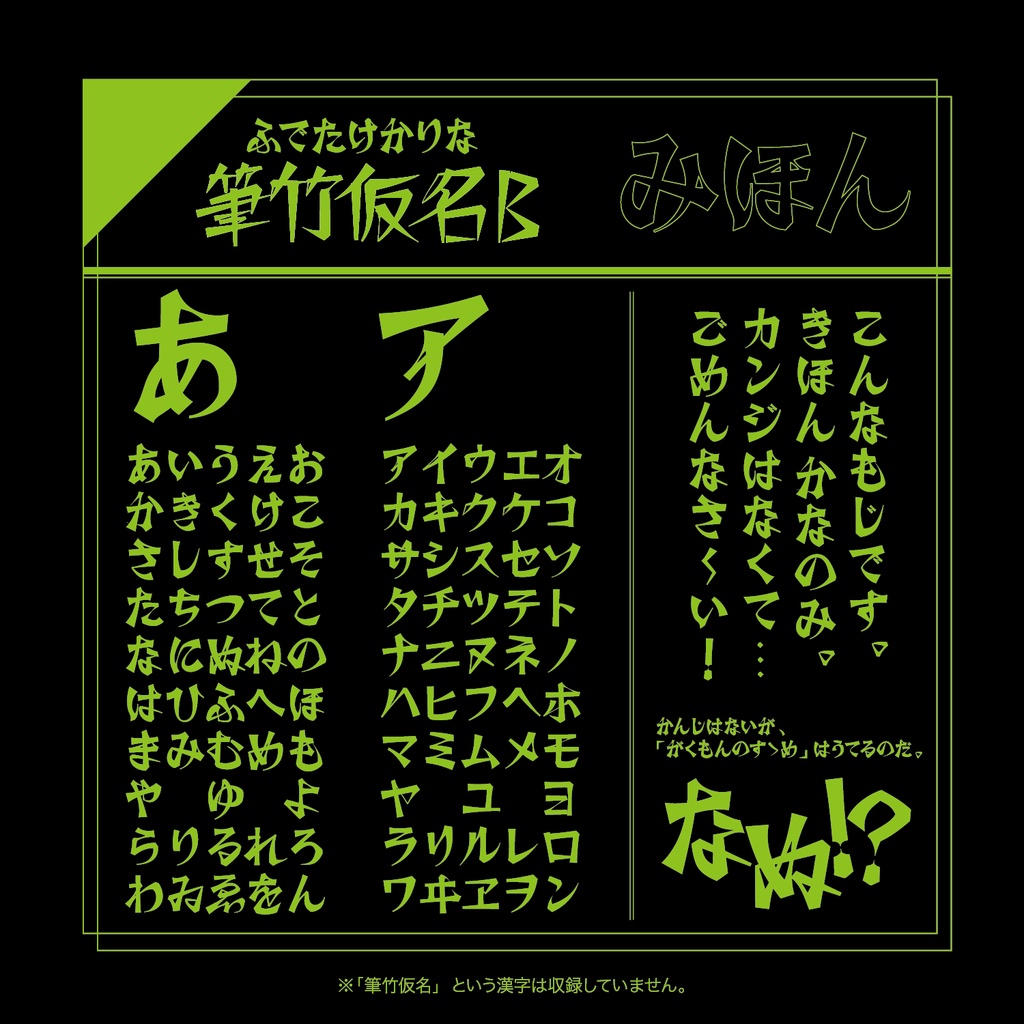
【フリーフォント】筆竹仮名B
<内容> ・「.otf」形式のフォント(Mac用) ・「.ttf」形式のフォント(Windows用) ・readme 【このフォントについて】 筆書体らしい運筆の特徴をもちつつ、ゴシック体のように角張ったパーツで構成されるフォントです。 かな書体のため、インパクトを持たせたい場面で部分的に使用すると効果的だと思います。 無償利用・商用利用問わず、自由にご使用いただけます。 印刷物のみならず、ゲームやWebなど何にでもご活用ください。 当フォントを利用した制作物などを、X(旧:Twitter)で報告していただけると、とても励みになります。 不具合の修正や新しいグリフの追加が行われていますので、最新のバージョンをご確認ください。 【すずみばと書林】 《もじピジョン》と《Suzumi Designs》による2人組のフォント制作ユニットです。 共同制作のフォントを配布・販売しています。 「書林」は本来「多くの書籍が集まるところ」という意味ですが、ここでは「多くの書体が集まるところ」という意味を込めて名付けました。 新作フォントの公開やバージョンの更新情報はそれぞれのTwitterでアナウンスしています。当フォントダウンロードの折には、フォローしていただけると幸いです。 《すずみばと書林/BOOTH》https://suzumi-bato.booth.pm/ 《もじピジョン/Twitter》https://twitter.com/Moji_Pigeon 《Suzumi Designs/Twitter》https://twitter.com/Suzumi_Designs +++++++++++++++++++++++++++++++++++++++++ 【収録文字】 ひらがな・カタカナ・欧文・一部約物 (最新ver.1.0) 【更新履歴】 ver.1.00 リリース 【利用規約】 ・利用条件 1)当フォントを使用したことによるいかなる損害も使用者自身が責任を負うものとします。 2)無償利用・商用利用ともにご自由にお使いいただけます。 3)クレジットの表記は不要です。 4)当フォントの二次配布は可能ですが、その際はこのtxtファイルを添付するようにしてください。なお、二次配布の際は一言いただけると幸いです。 5)当フォントを加工・変形してご利用いただけます。 6)ゲームやWebサイトに埋め込んでご利用いただけます。 ・禁止事項 1)当フォントを公序良俗に反する目的で使用することはできません。 2)当フォントを利用したロゴマーク等の商標登録はできません。 3)当フォントデータ・プログラムを、無断で改変したものを配布・販売することはできません。 4)当フォントの制作者を騙った発言等はできません。